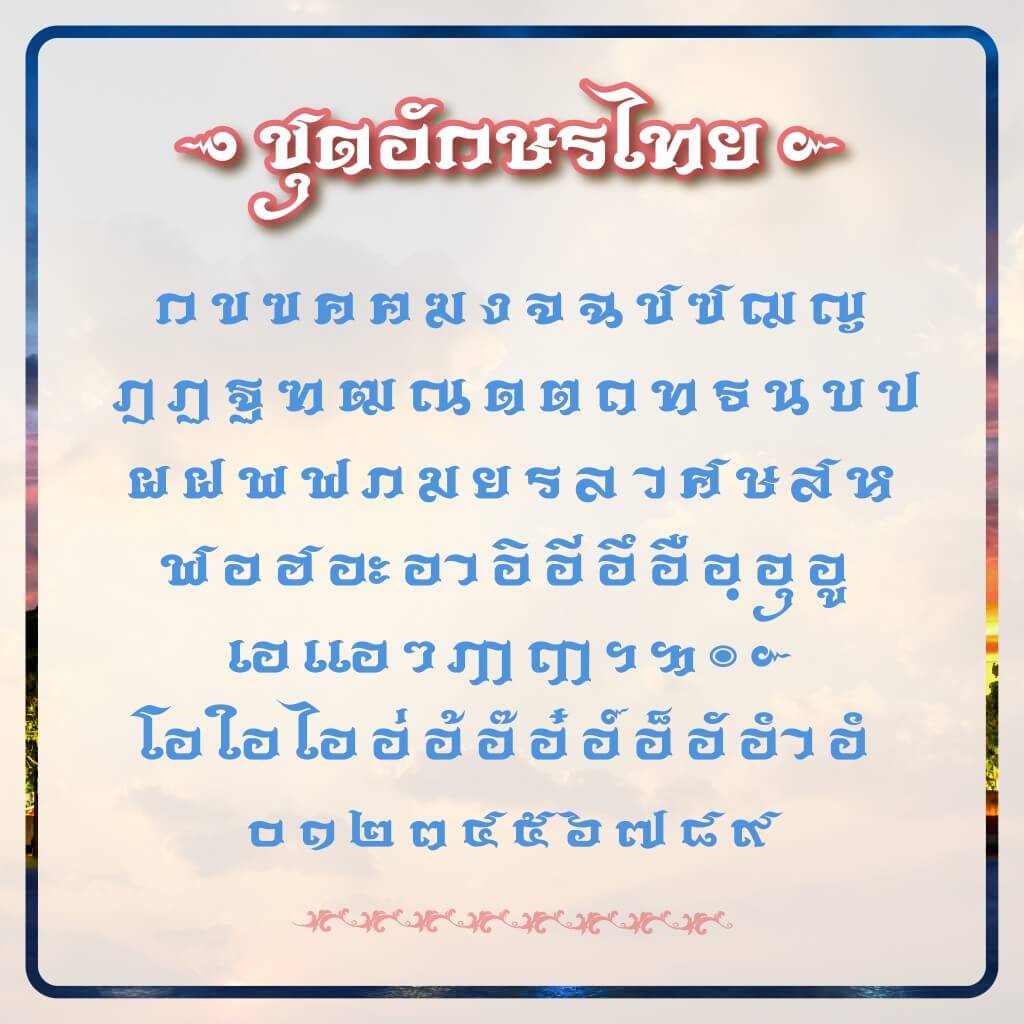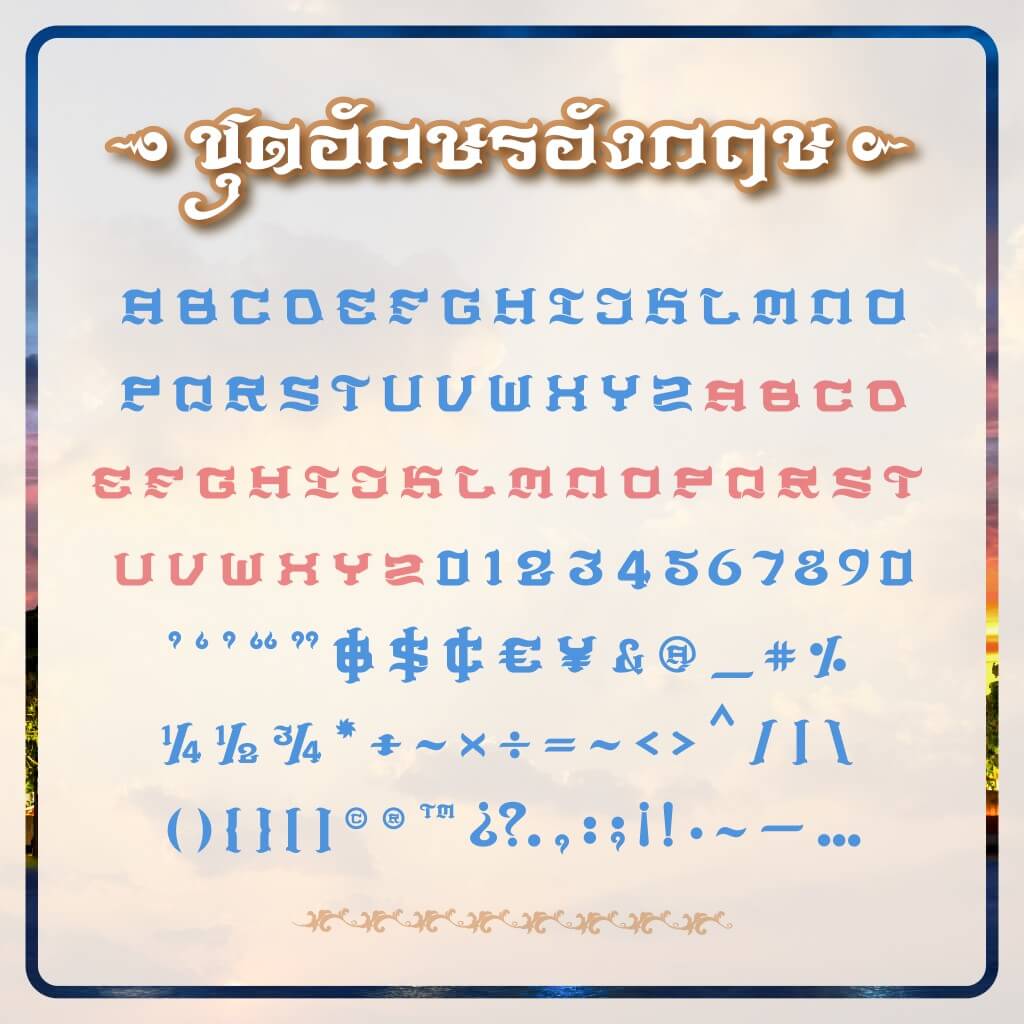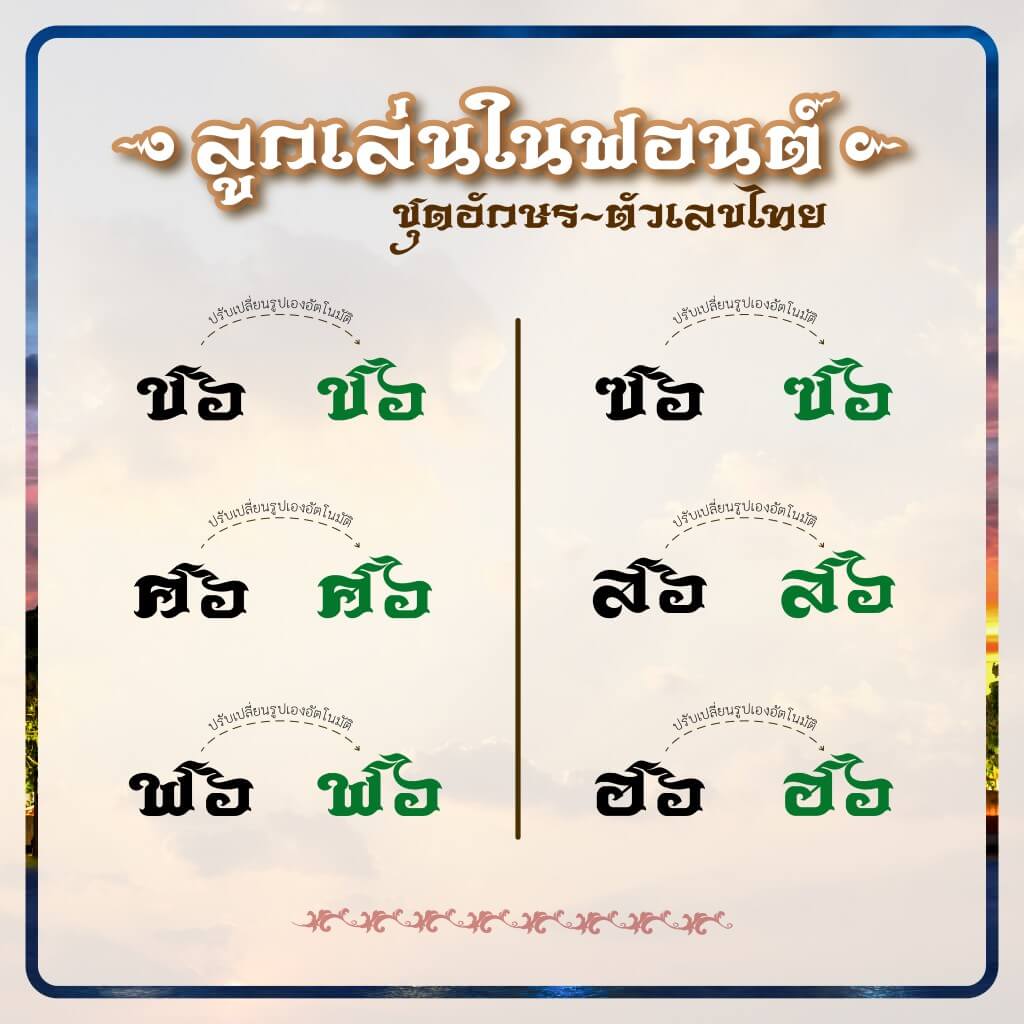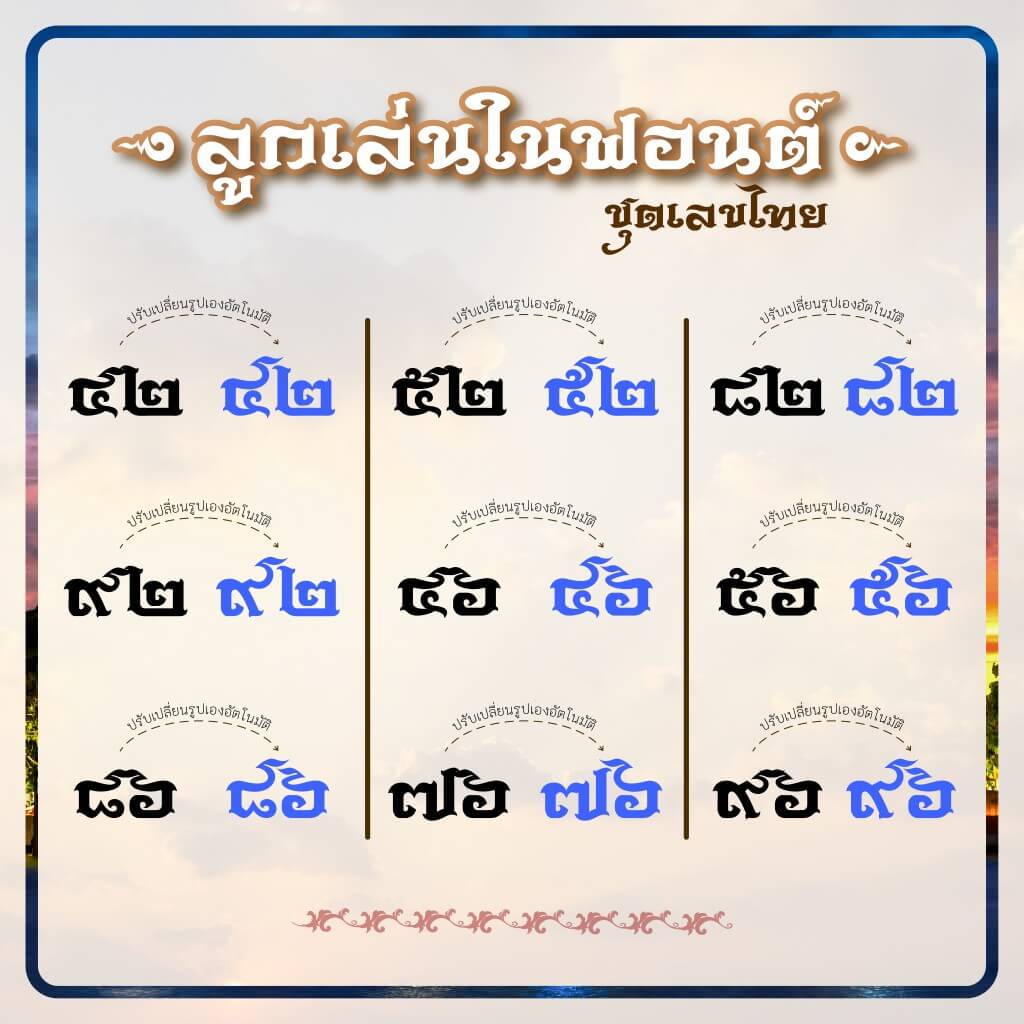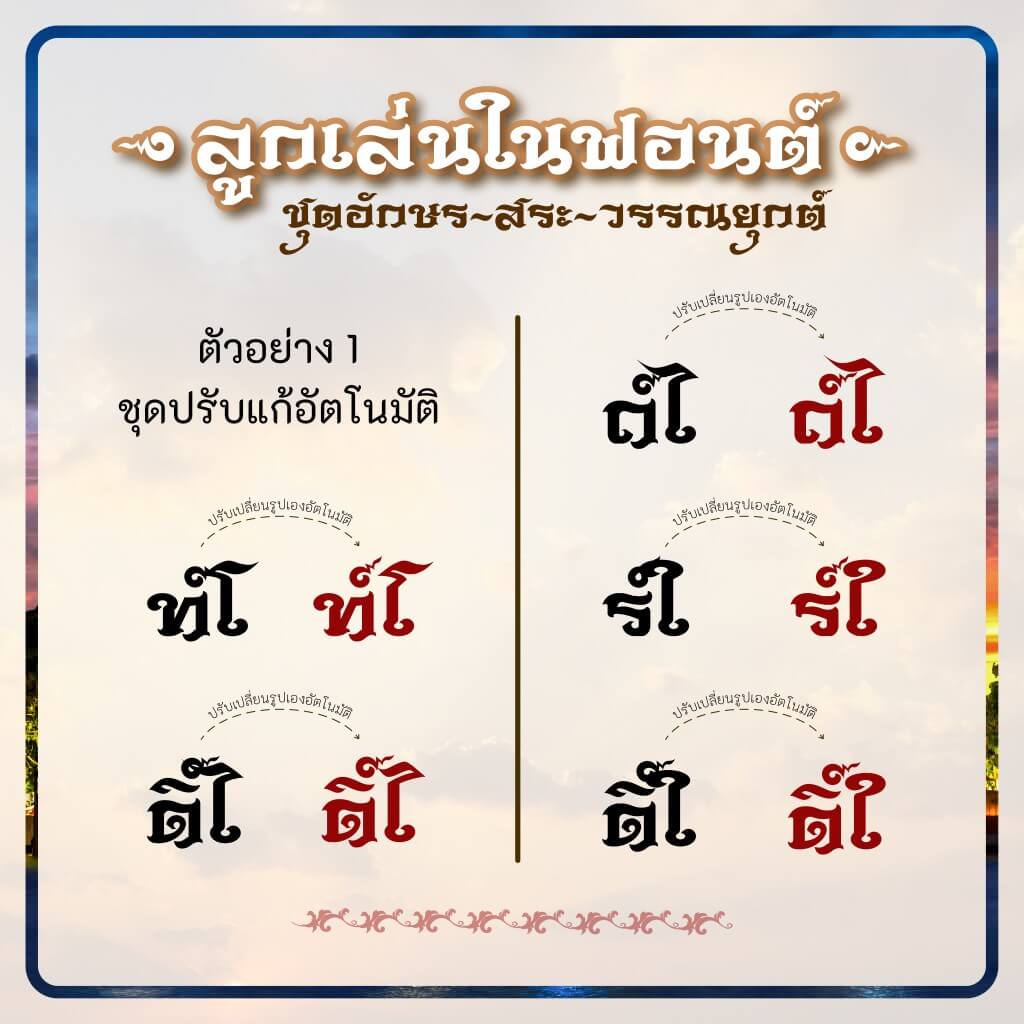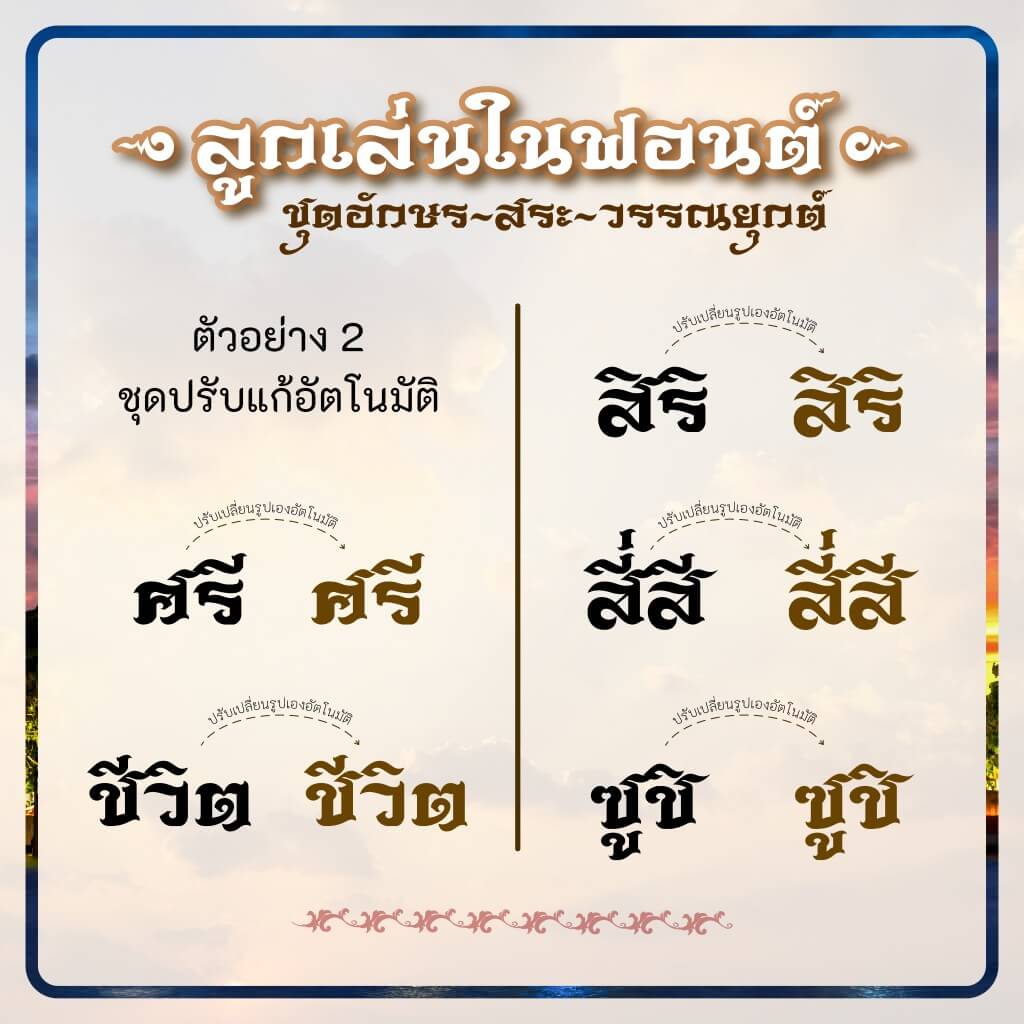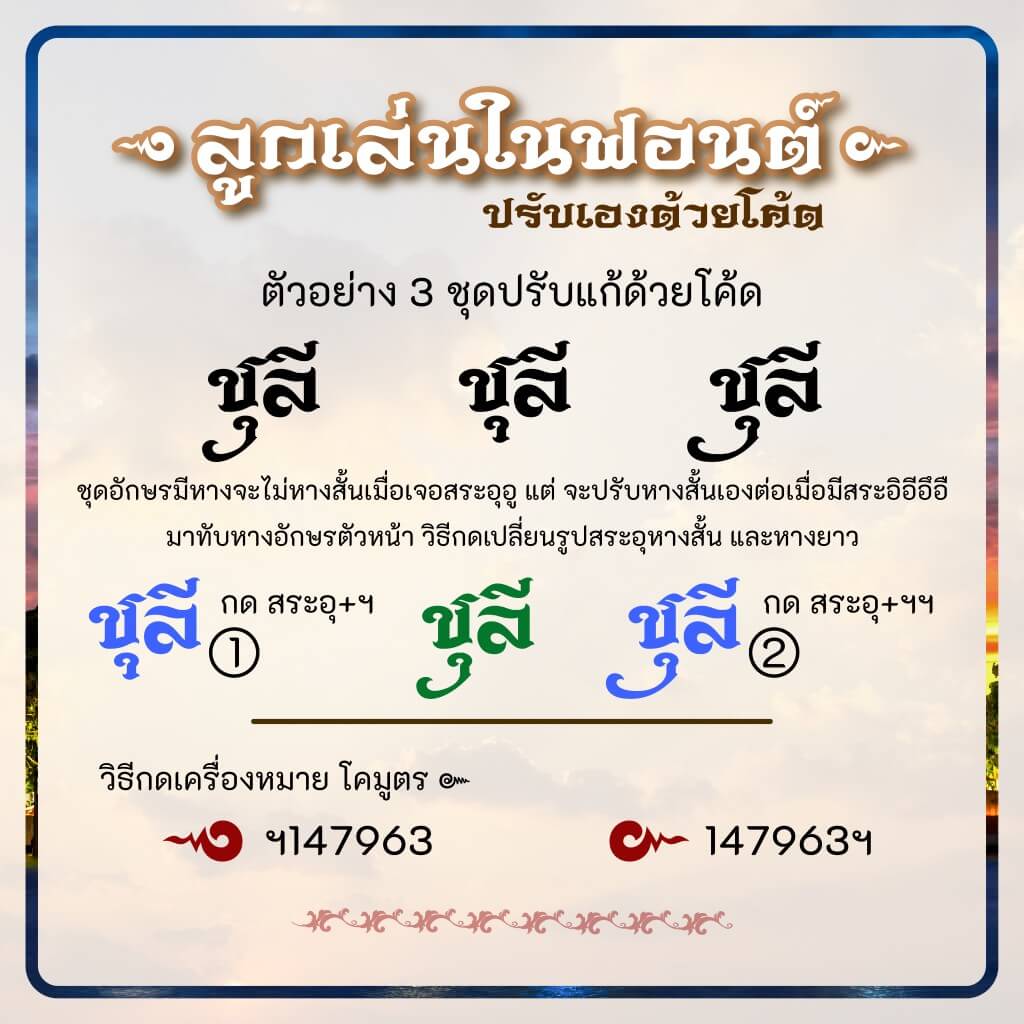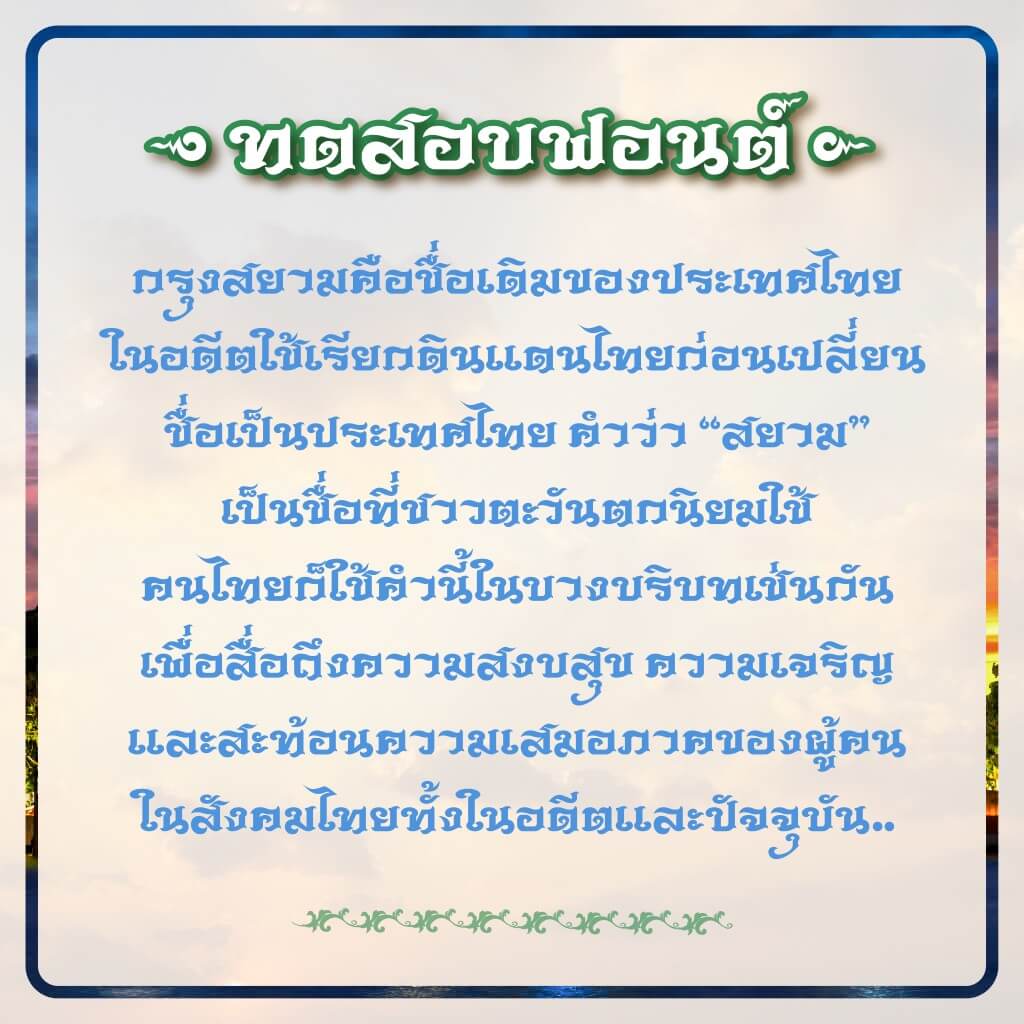
กรุงสยาม (j.devilfont@krung Siam)
นำเสนอผลงานฟอนต์ชุดที่ 12 กรุงสยาม ลักษณะฟอนต์ไทย พาดหัว หรือ งานป้าย งานไม้ งาน cnc บทกลอน ป้ายร้านค้า สายมู ปกนวนิยาย นิตยสาร พระเครื่อง ของโบราณ โลโก้ สกรีนเสื้อ แสดงความเป็นเอกลักษณ์ไทยร่วมสมัย ฯลฯ
รูปแบบอักษรไทย
รูปแบบอักษรอังกฤษ
ลูกเล่นในฟอนต์ กรุงสยาม -1
ลูกเล่นในฟอนต์ กรุงสยาม -2
ลูกเล่นในฟอนต์ กรุงสยาม -3
ลูกเล่นในฟอนต์ กรุงสยาม -4
ลูกเล่นในฟอนต์ กรุงสยาม -5
บทความทดสอบฟอนต์
รายละเอียดของฟอนต์กรุงสยาม
• ใช้งานด้วย kerning ปรับระยะห่างของชุดอักษรทั้งไทย-อังกฤษ
• ใช้ mark ในการจัด อักษร+สระ+วรรณยุกต์ เพิ่มการไล่ระดับสระ+วรรณยุกต์ อัตโนมัติ
• เพิ่มลูกเล่นที่ โ ใ ไ ที่ยืด-หด ความสูงในเวลาพิมพ์อัตโนมัติ
• ปรับหางสั้นเองเมื่อตัวอักษรมีหาง หรือสระอิอี ชนกันด้านหน้า-หลัง
• ชุด สระ วรรณยุกต์  ขยับเปลี่ยนไม่ให้ชนทับกับสระ วรรณยุกต์ ที่ตามหลัง
• ชุดตัวเลขไทย หางไม่ชนกันเพราะเปลี่ยนรูปแบบหางได้เองอัตโนมัติ
• เพิ่มวิธีการพิมพ์ โคมูตร ( ๛ ) กด ฯ147963 ต้องการโคมูตรตัวพิเศษกลับด้าน 147963ฯ
• เพิ่มวิธีการพิมพ์ตัวบาลี ญ ฐ แบบไม่มีเชิง ด้วยการกด ญฯฯ  /  ฐฯฯ  จะได้ตัวที่ไม่มีเชิง
• ยังมีลูกเล่นซ่อนอยู่อีก…ฯลฯ
ออกแบบโดย : เจ.ปีศาจฟอนต์